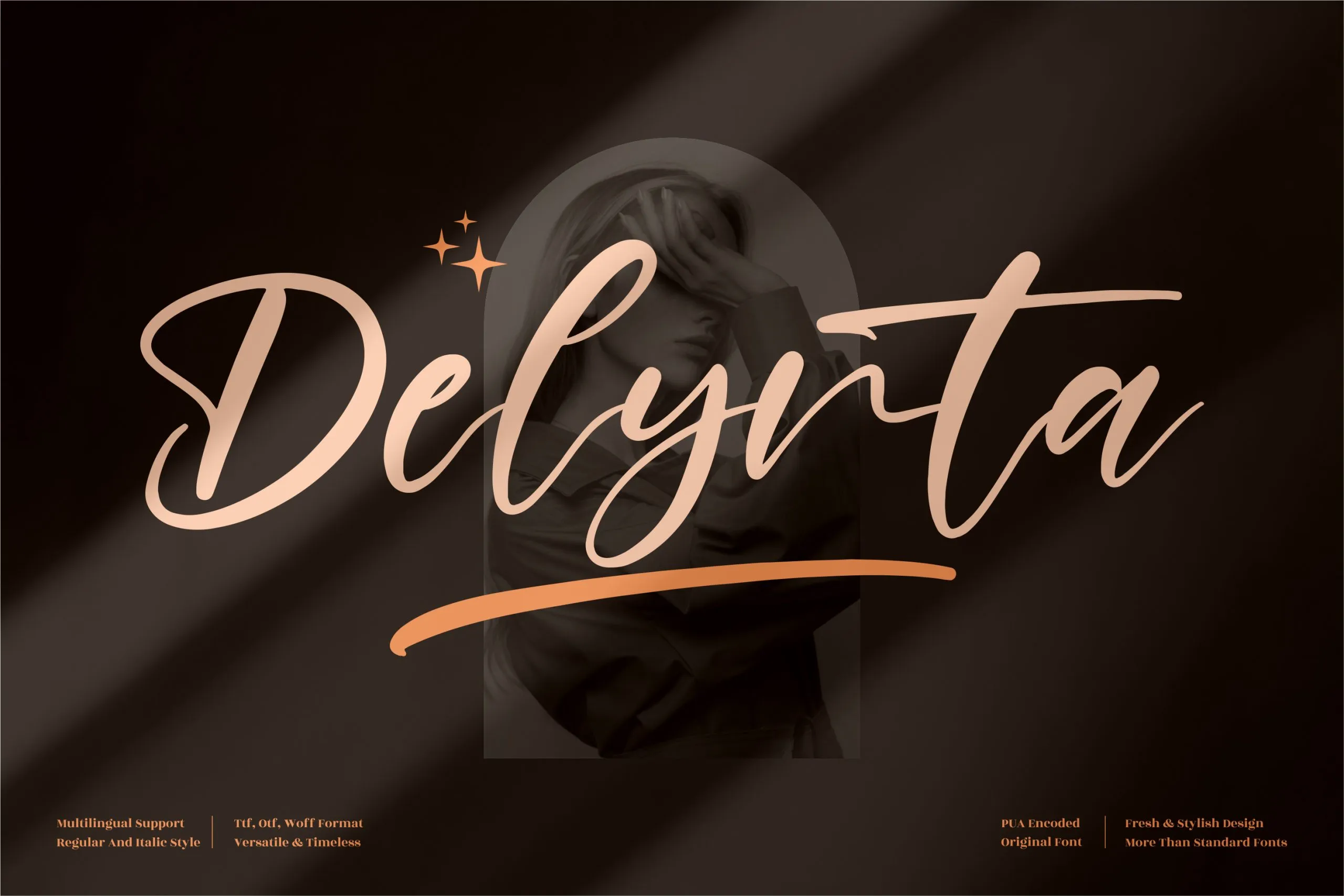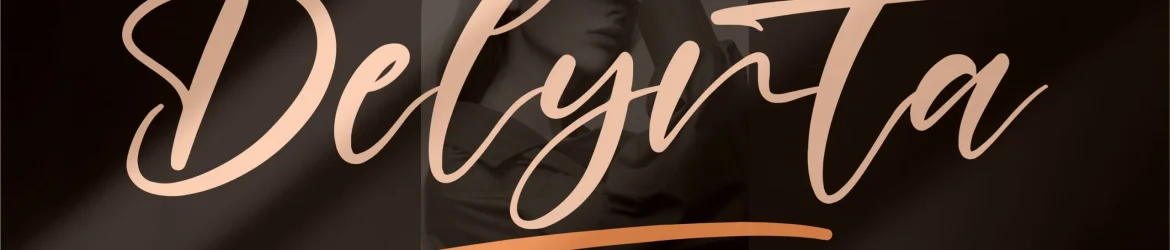
Delynta Font – Download Grátis
A fonte Delynta Font é uma escrita à mão perfeitamente adaptada para inúmeros projetos, tornando-a uma escolha irresistível para designers atentos ao detalhe. Seja para criar logotipos e embalagens de produtos finos, adesivos de caixa de chá personalizados, cartões de visita e convites, ou até mesmo capas de livros e painéis publicitários – Delynta é a fonte que você está procurando. Seu designer perspectype oferece uma experiência única com sua escrita à mão suave e charmosa, adequada para quem valoriza um toque pessoal em qualquer projeto. Escolha Delynta Font para adicionar uma personalidade especial a todos os seus projetos que exigem aquele toque de autenticidade.